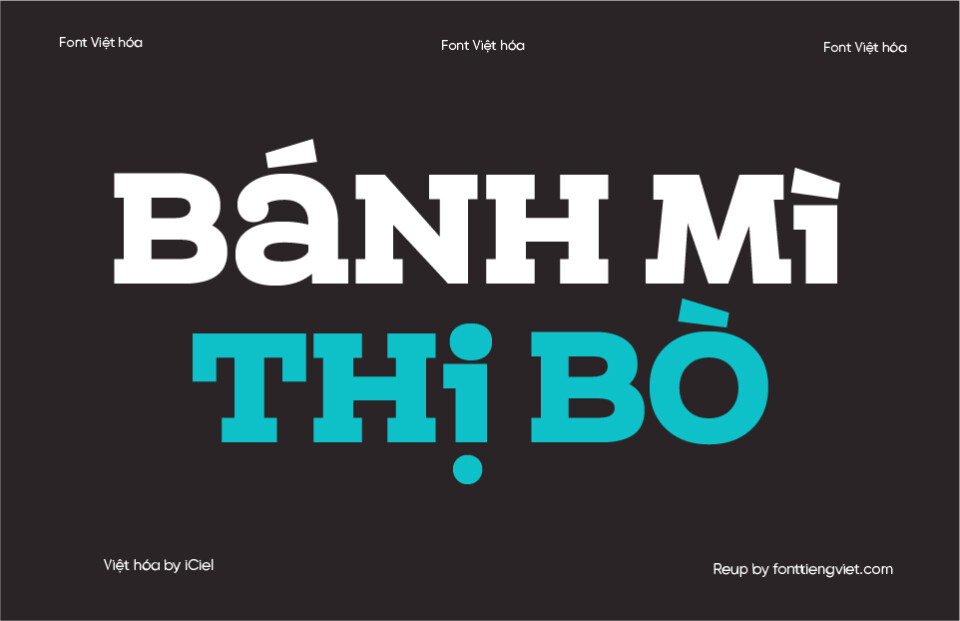
Font Việt hóa iCiel Queulat Uni
Trong thế giới đồ họa hiện đại, việc lựa chọn một bộ Font Việt hóa iCiel Queulat Uni chất lượng đóng vai trò quan trọng giúp sản phẩm trở nên chuyên nghiệp hơn. Đây là một bộ Font Miễn Phí được ưa chuộng nhờ sự kết hợp hài hòa giữa phong cách Slab Serif cổ điển và những nét hiện đại tinh tế. Với khả năng hỗ trợ tiếng Việt hoàn chỉnh, bộ font này giúp các bạn học sinh và giáo viên dễ dàng tạo ra những bài thuyết trình hay ấn phẩm học đường đẹp mắt mà không lo lỗi font chữ.
Đặc điểm nổi bật của Font Việt hóa iCiel Queulat Uni
Thiết kế độc đáo và linh hoạt
Bộ font này nổi bật với cấu trúc chân chữ vuông vức nhưng lại có những đường cong mềm mại ở các góc cạnh. Sự tương phản nhẹ nhàng này tạo nên một cảm giác ấm áp, gần gũi nhưng vẫn giữ được sự nghiêm túc cần thiết. Điều này giúp iCiel Queulat Uni trở nên cực kỳ linh hoạt trong nhiều bối cảnh khác nhau, từ việc thiết kế bìa sách, giáo án điện tử đến các biểu ngữ tuyên truyền trong nhà trường.
Tối ưu hóa cho người dùng Việt Nam
Điểm cộng lớn nhất chính là các dấu câu tiếng Việt được trau chuốt tỉ mỉ, đảm bảo tính thẩm mỹ cao nhất khi soạn thảo văn bản dài. Nhờ bảng mã Unicode chuẩn, bạn có thể sử dụng bộ chữ này trên hầu hết các phần mềm đồ họa phổ biến hiện nay một cách mượt mà.
Ứng dụng Font Việt hóa iCiel Queulat Uni trong học tập